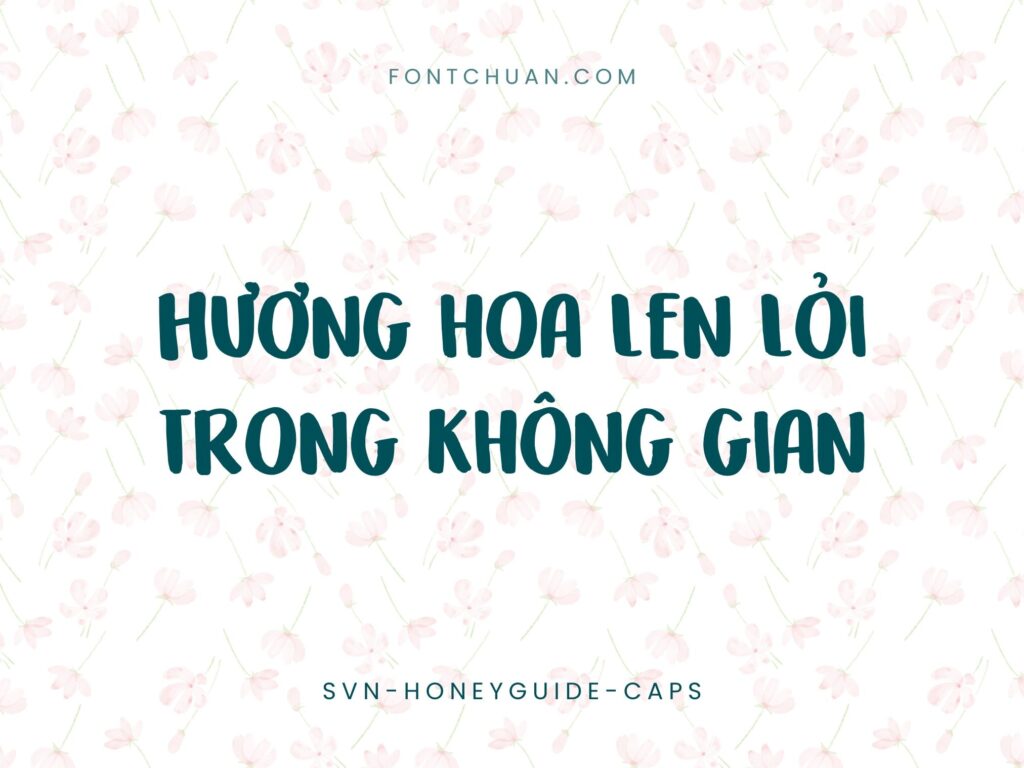
Font SVN Honeyguide Caps Việt Hóa
Tác giả Font: Hanoded
Honeyguide Caps là một kiểu Font chữ viết tay độc đáo, được thiết kế bởi David Kerkhoff và phát hành bởi Hanoded vào năm 2017. Phiên bản gốc của font này đã được Việt hóa bởi Styleno.1 Fonts, hỗ trợ đầy đủ tiếng Việt cùng hơn 100 ngôn ngữ khác. Thành viên của Font Chuẩn đã sưu tầm và chọn lọc font này nhằm đáp ứng nhu cầu đa dạng của bạn đọc và ứng dụng thực tế vào các dự án thiết kế.
Với phong cách viết tay tự nhiên và đường nét phóng khoáng, Honeyguide Caps cũng có thể được sử dụng như một Font chữ Halloween, mang lại cảm giác mộc mạc nhưng vẫn cá tính, phù hợp cho các thiết kế mang chủ đề lễ hội hoặc sự kiện sáng tạo. Honeyguide Caps có cấu trúc chữ in hoa với các nét vẽ tay tự nhiên, độ dày đều và độ tương phản nhẹ, tạo cảm giác thân thiện và gần gũi. Font này phù hợp cho các ứng dụng như thiết kế logo, tiêu đề, bao bì sản phẩm, thiệp mời và các dự án sáng tạo khác. Các ngành nghề như quảng cáo, spa, ẩm thực và thiệp cưới có thể tận dụng Honeyguide Caps để tạo điểm nhấn độc đáo trong thiết kế.